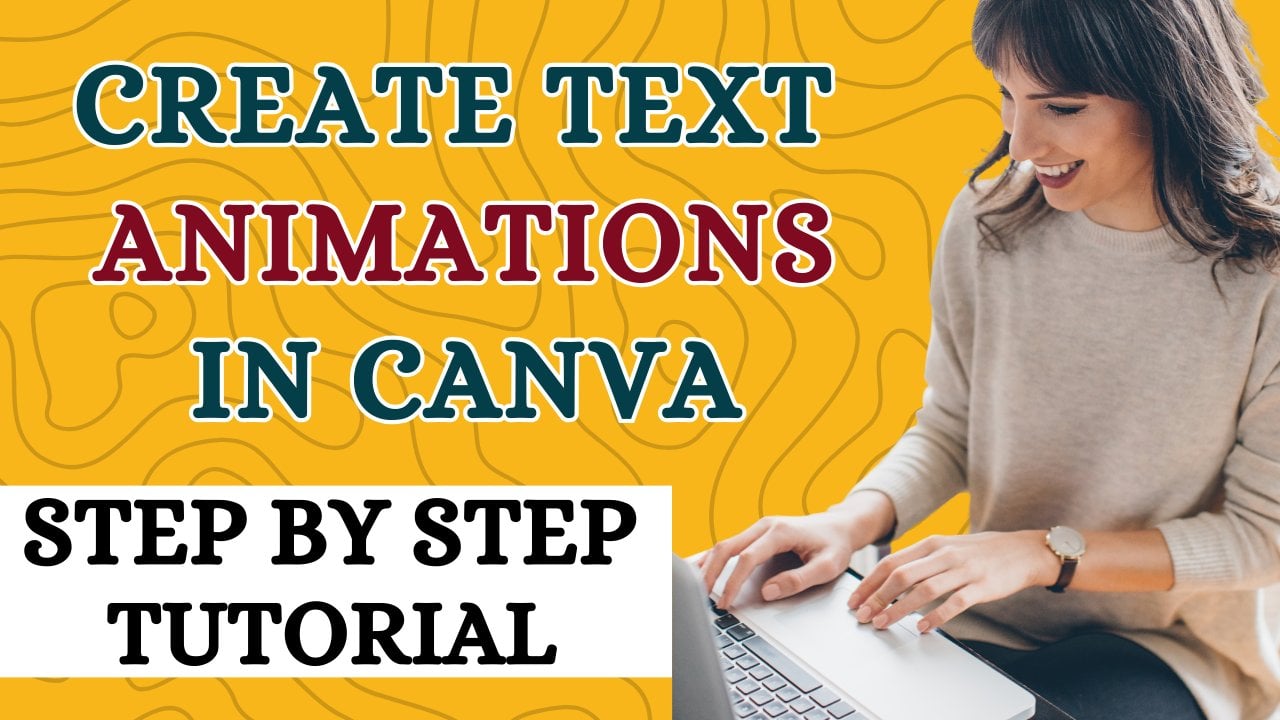
Canva für Anfänger: Lerne Canva-Textanimationen | Einfaches Canva-Tutorial für kinetische Typografie!
Einführung in die Typografie und ihre Typen
4 Prinzipien der Typografie
Animierte typografische Logos in Canva
Verwenden benutzerdefinierter Animationen bei der Logoerstellung
Anwenden benutzerdefinierter Animationen auf Vorlagen
Eine Pro-Technik zum Identifizieren von Schriftdetails
Hinzufügen von Audio zu typografischen Logos
Kursprojektvideo
Entdecke die Macht von Canva und tauche in die dynamische Welt der kinetischen Typografie mit unserem umfassenden Videokurs „Canva für Anfänger: Canva-Textanimationen lernen | Einfaches Canva-Tutorial für kinetische Typografie!“, Egal, ob du ein Anfänger bist oder über Designerfahrung verfügst, dieser Kurs ist darauf zugeschnitten, dass du mit den Fähigkeiten ausrüstest, um atemberaubende animierte typografische Logos mit Canva zu erstellen.
Kursübersicht: In diesem 9 Unterrichtseinheiten umfassenden Kurs führen wir dich durch die Grundlagen der Typografie, führen dich in die Kunst der kinetischen Typografie ein und bieten detaillierte Einblicke in die verschiedenen Arten. Mit dem Fokus auf der praktischen Anwendung baut jede Lektion auf der letzten auf und gipfelt in einem praktischen Projekt, in dem du deine neu gewonnenen Fähigkeiten zum Leben erweckst. Mit diesem Canva-Tutorial lernst du nicht nur Canva-Animationen, sondern machst auch einen Schritt auf dem Weg zum Canva-Pro!
1. Einführung in die Typografie und ihre Typen: Begib dich auf deine typografische Reise mit einer soliden Grundlage. Lerne mehr über die Geschichte der Typografie und erkunde ihre verschiedenen Typen. Verstehe die Bedeutung der Typografie im Design und entdecke, wie sie deine kreativen Projekte verbessern kann.
2. Kinetische Typografie aufgedeckt: Tauche ein in die fesselnde Welt der kinetischen Typografie. Verstehe, wie Text durch Bewegung zum Leben erweckt werden kann, und entdecke die Prinzipien, die eine effektive kinetische Typografie bestimmen. Lass dich von realen Beispielen inspirieren und begreife die Kunst des Storytellings durch bewegten Text.
3. Die 4 Prinzipien der Typografie: Meistere die Grundlagen der Typografie mit dem Fokus auf vier Schlüsselprinzipien: Ausrichtung, Kontrast, Wiederholung und Nähe. Entdecke wie diese Prinzipien zur Erstellung von visuell ansprechenden und wirkungsvollen typografischen Designs beitragen.
4. Erstellen animierter typografischer Logos in Canva: Hol dir praktische Erfahrung, während wir dich durch den Prozess der Erstellung animierter typografischer Logos in Canva führen. Lerne die Tools und Techniken, um deine Designs zum Leben zu erwecken und deine Logos in der digitalen Landschaft hervorzuheben.
5. Benutzerdefinierte Animationsfunktion von Canva: Erkunde die fortgeschrittenen Funktionen von Canva, insbesondere die benutzerdefinierten Animationstools. Entdecke wie du deine typografischen Animationen feinabstimmen und personalisieren kannst, um sicherzustellen, dass sie nahtlos an die Identität deiner Marke oder deines Projekts angepasst sind.
6. Verwenden benutzerdefinierter typografischer Animationen in Logo-Vorlagen: Integriere benutzerdefinierte typografische Animationen mühelos in bereits vorhandene Logo-Vorlagen. Lerne, wie du Vorlagen an deine einzigartige Vision anpassen und verbessern kannst, um Zeit zu sparen, ohne Abstriche bei der Kreativität zu machen.
7. Pro-Technik zum Identifizieren von Schriftdetails: Entdecke eine professionelle Technik zum Identifizieren von Schriftnamen und Familiendetails. Hebe deine typografischen Designs auf, indem du die perfekten Schriftarten auswählst, die mit deiner Marke oder Botschaft resonieren.
1. Klasse Trailer!: Willkommen Lernende. diesem neuen und spannenden Kurs über kinetische Typografie. Ich, Kartik Angrish, Assistenzprofessor für Management, zertifizierter Inhaltsstratege und erfahrener Willkommen zu diesem neuen und spannenden Kurs über kinetische Typografie. Ich, Kartik Angrish, Assistenzprofessor für Management, zertifizierter Inhaltsstratege und erfahrener Cope-Verräter. Ich habe Menschen in den Bereichen Schreiben digitaler Inhalte, Marketing und Grafikdesign geschult , insbesondere im Zusammenhang mit V. In diesem Kurs werde ich Ihnen beibringen, wie Sie die Leistungsfähigkeit von Kanva nutzen können, um atemberaubende animierte Logos zu erstellen, indem Sie die Prinzipien der kinetischen Typografie atemberaubende V. In diesem Kurs werde ich Ihnen beibringen, wie Sie die Leistungsfähigkeit von Kanva nutzen können, um atemberaubende animierte Logos zu erstellen, indem Sie die Prinzipien der kinetischen Typografie anwenden. Ich beginne mit einer Einführung in Typografie und ihre Typen, gefolgt von vier Prinzipien der Typografie mit einem besonderen Schwerpunkt auf kinetischer Typografie Dann werde ich zu animierten typografischen Logos in Canva übergehen typografischen Ich werde Ihnen beibringen, wie Sie benutzerdefinierte Animationen bei der Logo-Erstellung verwenden können benutzerdefinierte Animationen bei der Logo-Erstellung Anschließend werde ich mit Ihnen teilen, wie Sie die Leistungsfähigkeit der Vorlagen in Canva nutzen können , um sehr interessante benutzerdefinierte Animationen zu erstellen Am Ende dieses Kurses werde ich Ihnen eine professionelle Methode vorstellen, mit der Sie Ihre Schrift und ihre Familiendetails identifizieren können Im vorletzten Video werde ich mit Ihnen besprechen, wie Sie Ihren typografischen Logos Musik oder Audio hinzufügen können Ihren typografischen Logos Musik oder Audio hinzufügen Abschließend werde ich mit einem interessanten Projektvideo abschließen , in dem die Fähigkeiten, die Sie in diesem Kurs erworben haben, auf die Probe In diesem Kurs gibt es viel zu lernen. Ich freue mich auf dich in diesem Kurs. 2. Einführung in die Typografie und ihre Typen: Willkommen bei den Lernenden. Willkommen zu diesem Video zur Einführung in die Typografie ist ein sehr umfangreiches Thema, aber für den Zweck dieses Kurses werde ich mich auf die Typografie und ihre Grundprinzipien beschränken , die für die Leinwand relevant sind Es gibt bestimmte Dinge, die verstanden werden müssen, um das Beste aus diesem Kurs herauszuholen Lassen Sie mich zuerst Typografie definieren. Typografie ist ein Begriff, der für den Stil oder das Erscheinungsbild von Text verwendet wird für den Stil oder das Erscheinungsbild von Es ist auch bekannt als die Kunst , mit dem Text zu arbeiten. all diesen in Canva verfügbaren Schriftarten handelt es sich um voreingestellte typografische Sie haben es zur Erleichterung der Benutzer erstellt, damit Benutzer sie problemlos in ihren Text einprägen können Wenn ich zum Beispiel hier drüben klicke, wird diese spezielle Schrift hier angezeigt Ich kann die Größe ändern, die Farbe ändern, ich kann ihr Animationen hinzufügen, so oder so Ich kann dem typografischen Text hier auch einige Effekte hinzufügen. Vielleicht kann ich einen Glitch-Effekt aushöhlen oder hinzufügen, oder ich kann ihn neonfarben machen Ich könnte auch eine Gliederung hinzufügen. Ich kann auch diesen Lift - oder Spleißeffekt verwenden. Oder wenn ich keinen von ihnen haben möchte, kann ich zurück zur Nonne gehen, was der Standardeffekt ist Jetzt wissen Sie, was Typografie ist , und in Canva stehen zahlreiche Optionen zur Verwendung typografischer Elemente zur Verfügung Verwendung typografischer Elemente Lassen Sie mich die Typografie nun in zwei wichtige Segmente einteilen . Das eine ist Ihre statische Typografie, so wie dieser frische Text oder die hier geschriebene Typografie ein Beispiel für statische Typografie ist , bei der Sie eine bestimmte Schrift in einer bestimmten Farbkombination und in einem bestimmten Stil verwendet haben in einer bestimmten Farbkombination und in einem bestimmten Stil so wie dieser frische Text oder die hier geschriebene Typografie ein Beispiel für statische Typografie ist, bei der Sie eine bestimmte Schrift in einer bestimmten Farbkombination und in einem bestimmten Stil verwendet haben. Das ist es Sie können es als PNG-Datei oder als JPG-Datei herunterladen und es ist eine Bilddatei, die Sie verwenden können, wo immer Sie möchten. relevanter für diesen Kurs ist jedoch ein anderer Aspekt der Typografie, nämlich die typografische Animation oder kinetische Was genau ist kinetische Typografie? Lass es mich dir zeigen. Nehmen wir an, ich drücke die Schaltfläche „Animation abspielen“. Hier können Sie diesen Typografie-Text selbst sehen diesen Typografie-Text selbst der ein Beispiel für kinetische Typografie ist Sie können feststellen, dass es sich um eine Videodatei handelt und dass es sich um eine sich bewegende Abfolge von Zeichen handelt eine sich bewegende Abfolge Wenn ich es herunterlade, wird es als MP4-Datei oder als Datei im Videoformat heruntergeladen , nicht als statisches Bild. In diesem Kurs geht es genau um kinetische Typografie, insbesondere im Zusammenhang mit animierten Logos verwendet wird können Sie sehr beeindruckende Logo-Videodateien erstellen Mit Canva und den zahlreichen Funktionen Ich werde im Laufe dieses Kurses zu gegebener Zeit mehr über verschiedene Schriftarten und damit verbundene Themen sprechen Laufe dieses Kurses zu gegebener Zeit mehr über verschiedene Schriftarten und damit verbundene Themen . Ich denke, zur Einführung wissen Sie jetzt was genau Typografie ist und was ihre zwei Grundtypen sind, nämlich statische und kinetische Damit schließe ich dieses Video ab. Im nächsten Video werde ich über vier grundlegende Prinzipien der Typografie sprechen, über vier grundlegende Prinzipien der die sowohl für die statische als auch für die kinetische Typografie relevant sein werden . Stat Wir sehen uns im nächsten Video. 3. 4 Prinzipien der Typografie: Willkommen, willkommen zu diesem neuen Video. In diesem Video werde ich über vier Grundprinzipien der Typografie sprechen über vier Grundprinzipien der Typografie Was sind die vier Prinzipien der Typografie? Lassen Sie mich Ihnen die erste Hierarchie, Führung, Nachverfolgung und Unterschneidung erläutern . Was sind sie Lassen Sie mich nacheinander darauf eingehen, zunächst mit der Hierarchie beginne. Sie dient dazu, den Blick des Lesers zu lenken und Textabschnitten unterschiedliche Gewichte zu verleihen . Man kann die wichtigsten Abschnitte oben erwähnen und sie mit Felsbuchstaben, verschiedenen Stilen oder Farben oder allem zusammen hervorheben verschiedenen Stilen oder Farben oder allem zusammen hervorheben Apropos Führen: Führen ist einfach der Abstand zwischen den Zeilen Sie können sehen, dass zwischen diesen vier Zeigern, Hierarchie, Führung, Nachverfolgung und Urne, ein Leerzeichen diesen vier Zeigern, Hierarchie, Führung, Nachverfolgung und Urne, Die Anpassung dieses Abstands erfolgt durch den Prozess, der in Canva als Leading bezeichnet Es gibt eine sehr einfache Möglichkeit, dies zu tun. Wählen Sie einfach die Textelemente aus, die Sie anpassen möchten, und gehen Sie zur Option Abstand. Hier gibt es sowohl die Option des Buchstabenabstands als auch des Zeilenabstands. Wir beziehen uns auf Leading , also auf Zeilenabstand. Sie können sehen, dass ich es von hier aus anpassen kann. Der Abstand zwischen den Linien nimmt zu. Sie kann auch von hier aus verringert werden. Diese Funktion ist ein nützliches Feature. Wenn Sie bestimmte Schriften verwenden, die in ihrem Design, in ihrem Stil zu überladen ist ein nützliches Feature. Wenn Sie bestimmte Schriften verwenden sind, benötigen sie mehr Abstand zwischen den Zeilen, benötigen sie mehr Abstand zwischen um den Text lesbarer und lesbarer zu machen eleganter Zeilenabstand wird auch als Zeilenabstand bezeichnet Dies ist ein wichtiges Prinzip der Typografie, das Sie beachten müssen Als nächstes folgt das Tracking. Tracking ist eine Ergänzung zum Führen. Tracking ist nichts anderes als Ihr Buchstaben - oder Zeichenabstand. In Canva nennen wir das Buchstabenabstand. Wenn ich ihn von hier aus anpasse, kann ich den Abstand zwischen den Zeichen vergrößern oder verkleinern Auch hier besteht der Zweck darin, Ihren Inhalt zu gestalten, Ihren Text lesbarer, schöner und augenschonender zu Diese beiden wichtigen Prinzipien sind wichtige Elemente der Typografie Das heißt, Leading und Tracking lassen sich in Canva mithilfe der Funktion „Abstand“ ganz einfach in Canva mithilfe der Funktion „ Nachdem das Führen und Nachverfolgen von Hierarchien nun abgeschlossen ist, an vierter Stelle die Unterschneidung. Was genau ist Kerning? Ist sehr eng mit dem Tracking verwandt, es geht aber um Verzerrungen im Abstand Es gibt bestimmte Formen, bei denen ein Abstand zwischen verschiedenen Zeichen besteht , was beim Verkleinern sehr unangenehm aussieht Sie möchten nicht in einer Position sein, in der Sie ein Dokument erstellen, und wenn ein Text einmal verkleinert ist, wirkt er unprofessionell und unattraktiv wirkt er Dieser unvollkommene Abstand zwischen den Zeichen wird auch als schlechter Ring bezeichnet auch Wenn Sie auf eine Schrift stoßen, die schlecht ausgehärtet ist, sollten Sie auf jeden Fall versuchen , diese Schriftart zu ändern, da Sie dadurch möglicherweise nicht die gewünschten Ergebnisse erzielen Seien Sie vorsichtig bei schlechten Schriften. Sie müssen sehr vorsichtig sein dass Leerzeichen zwischen den Zeichen, wie zum Beispiel in dieser speziellen Schrift, hat sie ein sehr gutes n, bedeutet, dass der Abstand zwischen E und E, N, N und N, G alle gleich Es sieht nicht komisch aus, wenn ich es herauszoome. Selbst dann stirbt es nicht, das meine ich Du solltest also bei der Auswahl deiner Schriften sehr vorsichtig sein, damit deine Schriften keine böse List haben dürfen Das sind die vier Prinzipien der Typografie. Ich hoffe, Sie haben sie verstanden und sie werden sich als sehr nützlich erweisen, wenn Sie anfangen, mit kinetischer Typografie zu arbeiten Im nächsten Video werde ich über typografische Logoanimationen in Canva oder die Erstellung kinetischer Typografie mit Canva speziell für die Erstellung dynamischer Logos sprechen typografische Logoanimationen in Canva oder die Erstellung kinetischer Typografie mit Canva speziell für Danke, dass du dir das angesehen hast, lerne weiter. Schau weiter zu. Wir sehen uns im nächsten Video. 4. Animierte typografische Logos in Canva: Willkommen, Lernende. Willkommen zu diesem neuen Video In diesem Video werden wir darüber sprechen, wie wir die Leistungsfähigkeit von Canva nutzen können , um kinetische Typografie für die Erstellung animierter Logos zu erstellen für die Erstellung Va unterstützt eine Vielzahl von Grafiken und Animationen, und kinetische Typografie oder kinetische Logos oder animierte Logos Wie Sie sehen können, verfügt Canva über viele integrierte Animationen für typografische Elemente, mit denen werden können Wir werden sie nacheinander untersuchen, was sie sind und wie du die Leistungsfähigkeit dieser integrierten Animationen nutzen kannst , um atemberaubende kinetische Logos in Canva zu erstellen Lassen Sie mich ein hypothetisches Logo für eine Firma namens Kinetic Yoga erstellen eine Angenommen, dies ist der Name unseres Unternehmens und wir müssen ein animiertes Logo für dieses Unternehmen erstellen Was wir tun werden, ich habe hier Kinetic Yoga mit einfachen Textelementen geschrieben hier Kinetic Yoga mit einfachen Textelementen Was ich damit machen kann, ich wähle einfach zuerst die Effekte aus, um dem Ganzen ein einzigartiges Aussehen und Gefühl zu verleihen Ich sage vielleicht Gliederung, oder das sieht gut aus. Ich kann hier sogar andere Elemente ausprobieren, aber dieser Spleiß sieht gut aus Lassen Sie mich das nur ein wenig vergrößern. Das sieht gut aus. Lass es mich einfach in die Mitte stellen. Bei diesem Text kann ich den Abstand anpassen , da Ihr Logo kompakt sein sollte. Lassen Sie mich den Raum ein wenig reduzieren. Erinnern Sie sich an die grundlegenden typografischen Prinzipien , die ich im vorherigen Video mit Ihnen besprochen habe Lassen Sie mich hier einfach den Abstand zwischen den Buchstaben reduzieren . Das sieht gut aus. Nun, was ich hier tun kann, ich kann einfach auf diese Animate-Schaltfläche klicken Ich werde zu diesem Animationsregal auf Canva weitergeleitet, wo ich meine gewünschte Animation auswählen kann Beachten Sie, dass zwei Arten von Animationen verfügbar sind. Hier sind Animationen auf Seitenebene und eine weitere sind Textanimationen. Wenn ich auf die Seitenanimation klicke, wird alles, was sich auf der Seite befindet als solches animiert. Angenommen, ich hätte zwei Logos , nur um den Seitenanimationseffekt hier zu präsentieren. Da ich kinetisches Yoga hier dupliziert habe, möchte ich noch einmal auf Animation klicken Und ich werde hier auf die Seitenanimation klicken. Welche Animation ich nun auch anwenden werde, sie wird gleichzeitig auf die gesamte Seite angewendet. Das sind die beiden kinetischen Yoga-Elemente, die es gibt. Sie können von hier aus sehen, dass jede Animation, die ich auswähle, auf beide Zeilen hier angewendet wird Das ist der Vorteil von Animationen auf Seitenebene, aber normalerweise hat man nicht mehrere Zeilen. Animationen auf Textebene reichen für Sie aus, falls Sie mehr als zwei Elemente haben. Animationen auf Seitenebene können in Canva sehr praktisch sein. Lass mich das löschen. Den brauchen wir nicht. Nun, mit dem, was ich machen kann, vielleicht könnte ich hier ein Bild haben. Dies ist ein in die engere Wahl gezogenes Bild dieser hypothetischen Firma, Kinetic Yoga Nehmen wir an, das Bild, das ich habe, ist der Text, den ich in meinem Logo Lassen Sie mich sie einfach gruppieren , damit ich sie leicht in der Größe ändern kann Nun, das sieht schon sehr gut aus, aber es ist ein statisches Logo Was wir wollen, wir wollen ein animiertes Logo. Das ist ein Logo im Videoformat. Was wir damit machen können, ich werde diese Gruppe gemeinsam auswählen und hier zum Tab wechseln. Jetzt wird diese gesamte Gruppe animiert , da alle Elemente zusammen gruppiert wurden. Lassen Sie mich dorthin gehen und nehmen wir an, dass ich das wieder benutze. Beachten Sie nun, dass es früher Seitenanimationen und Textanimationen gab. Nun, was ist hier passiert? Die Registerkarte „Textanimation“ wurde automatisch durch eine Fotoanimation ersetzt. Da ich ein Foto zu meinem Logo-Regal hinzugefügt habe, kann ich, wenn ich nur ein Foto animieren möchte, dieses auswählen Andernfalls kann ich die Seitenanimation verwenden, die sich sowohl auf den Text als auch auf das Foto auf der Seite auswirkt Angenommen, ich möchte dieses oder jenes auswählen. Ich kann jeden von ihnen auswählen. Es sind viele Animationen verfügbar. Ich kann mich für eine von ihnen entscheiden. Diese Kombinationen sind zwar ziemlich mächtig und ziemlich elegant, aber ich bin nicht auf sie beschränkt. Ich kann sie jederzeit mit den unten angegebenen Optionen anpassen. Angenommen, ich möchte mich mit der Geschwindigkeit der Animation befassen. Ich kann es von hier aus machen. Ich kann es je nach Fall langsamer oder schneller machen. Es liegt an mir. Ich kann auch wählen, ob ich an beiden Enden animieren möchte. Das heißt, sowohl am Anfang als auch am Ende oder nur beim Betreten oder beim Verlassen Hier gibt es ziemlich viele Variationen. Es gibt hier sogar eine Richtungsvariation, die ich ändern kann, das ist eine Standardrichtung, Richtung nach oben. In dieser speziellen Animation kann ich es nach unten machen, indem ich mich für diesen Pfeil hier entscheide Ich kann diese Optionen hier weiter anwenden , die wenig fortgeschritten sind Aber auch hier geben sie mir die Möglichkeit, mit verschiedenen Bewegungen zu spielen . Sowohl mein Text als auch Fotoelemente sind in meinem Logo enthalten. Diese Ausscheidungen sind hier ganz nett wie Sie von hier aus sehen können Das sieht toll aus, nicht wahr? Auch hier kann ich die Bewegung der ausgeführten Animationen beurteilen , indem ich diese Pfeiltasten verwende, um ihr mehr Abwechslung zu verleihen Sie haben Ihnen die Möglichkeit gegeben diese Bewegungseffekte hinzuzufügen Sie können diesen Rotationseffekt haben. Siehst du, wie toll es aussieht, nicht wahr? Sie können auch einen Flackereffekt, Pulseffekt oder einen Wackeleffekt Erstaunlich, nicht wahr? So können Sie diese animierten Logos mit Canva ganz einfach erstellen diese animierten Logos mit . Wählen Sie einfach den Text und das entsprechende Bild aus Wenn Sie sie möchten, fügen Sie einfach gewünschten Effekt hinzu oder Ihre Schriftart ist gut genug Sie müssen keine gleichmäßigen Effekte hinzufügen Wenden Sie auch einfach eine der eingebauten Animationen an. Hier können Sie sowohl Animationen auf Seitenebene als auch auf Foto - oder Textebene ausprobieren Animationen auf Seitenebene als auch auf Foto - oder Textebene Und was auch immer Ihrem Zweck am besten dient , Sie können es versuchen Es gibt viele Variationen und du kannst sie anhand ihrer Richtung, ihrer Geschwindigkeit und anderer Filter, die sie dir hier gegeben haben, weiter anpassen ihrer Geschwindigkeit und anderer Filter, die sie dir hier gegeben haben So einfach ist es, atemberaubende animierte Logos in Canva zu erstellen atemberaubende animierte Logos in Canva Mit den integrierten Animationsoptionen können Sie jede Art von Logo erstellen gibt es zwar viele Optionen Canva gibt es zwar viele Optionen zum Erstellen animierter Logos Wenn Sie jedoch Ihre eigene Version der Animation erstellen möchten , gibt es dennoch einen Ausweg Im nächsten Video werde ich mit Ihnen besprechen, wie Sie relativ einfach benutzerdefinierte Animationen in Canva erstellen können relativ einfach benutzerdefinierte Animationen in Canva erstellen Wenn Sie es mit anderen komplexen Grafikdesign-Softwares vergleichen , können Sie sich etwas Eigenes einfallen lassen, etwas sehr Einzigartiges, das möglicherweise für Ihren Geschäftszweck erforderlich ist Danke, dass Sie sich das angesehen haben. Lernen Sie weiter, schauen Sie weiter Wir sehen uns im nächsten Video. 5. Verwenden von benutzerdefinierten Animationen bei der Logo-Erstellung: Willkommen, Lernende. Willkommen zu diesem neuen Video In diesem Video werde ich mit Ihnen besprechen, wie Sie die benutzerdefinierte Animationsfunktion von Canva verwenden können , um atemberaubende kinetische Logos zu erstellen Mal sehen, wie wir das machen können. Im letzten Video habe ich mit Ihnen besprochen, wie diese Animationen funktionieren, sowohl auf Elementebene als auch auf Seitenebene. Jetzt werde ich Ihnen eine weitere beeindruckende Funktion von Animationen in Canva vorstellen eine weitere beeindruckende Funktion von , nämlich benutzerdefinierte Animationen Mal sehen, wie wir das machen können. Wenn ich ein Element auswähle, wenn ich mehrere Elemente oder eine Seite als Ganzes auswähle, gibt es hier die Möglichkeit, die Animation zu schwenken. Wir kennen diesen Bereich inzwischen, aber es gibt noch eine weitere Option, um oben eine Animation zu erstellen. Dies ist eine benutzerdefinierte Animationsfunktion von Canva. Es ist eine sehr leistungsstarke Funktion. Es gibt Ihnen die Möglichkeit, Ihre eigene Version von Animationen gemäß Ihren Anforderungen und Ihrer Kreativität zu erstellen. Mal sehen, wie es funktioniert. Angenommen, ich wähle hier dieses einzelne Element aus und klicke auf Registerkarte Animation erstellen. Es gibt mir die Möglichkeit, meinen eigenen Animationspfad zu entwerfen. Ich kann diesen Text nach meinen eigenen Wünschen und meiner Kreativität verschieben , ihn platzieren, wo immer ich will, und dieser Pfad wird als animierter Pfad nachgezeichnet Sie können sehen, wie dieser animierte Pfad funktioniert. Nun, das war nur, um Ihnen darüber zu erzählen Beachten Sie das hier, da ich im Animations-Tab einen benutzerdefinierten Animationspfad ausgewählt hatte , ist er hier benutzerdefiniert geschrieben. Wenn mir das nicht gefällt, kann ich es sicherlich ändern. Angenommen, ich möchte den Pfad löschen. Ich kann es einfach von hier aus machen. Das Element, für das der Animationspfad gelöscht werden muss, muss ausgewählt werden. Ich habe hier kinetisches Yoga ausgewählt. Und ich werde diesen Pfad auf einmal löschen. Der gesamte Pfad wurde auf die Standardwerte zurückgesetzt. Das heißt, hier gibt es keine Animation. Wie Sie sehen können, ist es animiert geschrieben. Anstatt benutzerdefiniert bedeutet das, dass keine Animation im Spiel ist Auch hier kann ich dasselbe auf mehrere Elemente anwenden . Lass es mich dir hier ganz schnell zeigen. Ich wähle hier beide Elemente aus und klicke auf die Option Animieren. Und dann gehe ich zur Animation erstellen. Von hier aus wähle ich einen Pfad für alle Elemente zusammen aus. Jetzt sieh dir das an, lass es mich für dich spielen. Siehst du das, wie es funktioniert? Dies diente nur dazu, die Funktionalität dieses benutzerdefinierten Animationspfads zu demonstrieren . Nun stellt sich die Frage, wie man es effektiver einsetzen kann, um professionelle, großartige und dennoch einzigartige benutzerdefinierte Animationen zu erstellen . Wir werden in diesem Video darüber sprechen. Jetzt habe ich dieses kinetische Yoga hier ausgewählt. Ich möchte es nicht nach dem Zufallsprinzip bewegen , weil es nicht professionell aussieht Was ich tun werde, ich werde hier eine weitere Funktion anwenden. Lassen Sie mich jetzt einfach die Schritte hier durchgehen , damit ich eine Umschalttaste auf meiner Tastatur gedrückt halten und diese dann bewegen kann. Es wird sich in der geraden Linie bewegen. Wenn ich es sanft in eine der beiden Richtungen bewege, nehmen wir an, ich bewege es nach Norden, dann können Sie sehen, dass es sich um eine gerade Linie Ich bringe es langsam in die ursprüngliche Position zurück und belasse es dort Sehen Sie sich jetzt an, wie diese Animation funktioniert. Das ist viel besser als die zufällige Bewegung. Gut, nochmal, ich lösche diesen Pfad. Ein weiteres wichtiges Merkmal der benutzerdefinierten Animation. Wie bei anderen Animationen , die wir bisher gesehen haben, können wir sie hier in Verbindung mit den Bewegungseffekten verwenden . Lassen Sie mich Ihnen zeigen, wie wir das machen können. Nehmen wir an, ich wähle dieses Foto hier und gehe dann zur Schaltfläche Animieren, und da drüben gibt es Bewegungseffekte. Gut, was ich tun werde, ich werde einen der Bewegungseffekte anwenden Ich kann mehrere Bewegungseffekte anwenden. Siehst du, ich habe „Flackerperlen drehen“ ausgewählt. Ich kann dem sogar Wackeln hinzufügen und einfach sehen, wie es funktioniert. Es sind mehrere Bewegungseffekte im Spiel. Aber auch hier übertreibt es die Dinge. Es ist nicht ratsam, was ich tun werde, ich wähle hier einen Bewegungseffekt und entferne alle anderen Bewegungseffekte Lass mich wackeln. Ich entferne auch den Rotationseffekt. Sie müssen jeden Effekt einzeln entfernen. Ich werde entweder den Puls halten oder flackern. Angenommen, ich habe mich für Flicker entschieden. Mit Flicker geht es so, oder ich kann den Puls halten und das Flimmern entfernen Jetzt wird es so aussehen. Das sieht besser aus. Lass mich diesen Pulseffekt behalten. Gehen Sie jetzt zur Option Animieren. Klicken Sie auf Animation erstellen, benutzerdefinierte Animation und drücken Sie die Umschalttaste Jetzt werde ich dieses kinetische Yoga ein wenig nach oben bewegen. Ich klicke hier auf Fertig und sehe, wie es ganz sanft herauskommt Dieser kinetische Yoga-Text bewegt sich ein wenig nach oben und gleichzeitig pulsiert dieses Bild zusammen Mit diesen beiden Effekten erhalte ich eine professionell aussehende Animation Lassen Sie mich Ihnen zeigen, wie es funktioniert. Lass mich einfach diese kinetische Yoga-Animation verbessern. Ich bringe es auch wieder an die ursprüngliche Position , damit es wieder an seinen ursprünglichen Platz kommt Lassen Sie mich hier auf die benutzerdefinierte Animation klicken. Ich werde den Pfad löschen. Und jetzt drücke ich erneut die Shift-Taste und bewege sie leicht nach oben. Und bringe es in der geraden Linie nach unten , während du die Shift-Taste gedrückt hältst. Nun sieh mal, so kommt es. Lassen Sie mich jetzt einfach die Geschwindigkeit dieser Animation erhöhen. Ich kann die Geschwindigkeit von benutzerdefinierten Animationen steuern , wie ich es mit den anderen Animationen tun kann. Ich werde die Geschwindigkeit erhöhen weil es ein bisschen ruckelig ist Und das liegt daran, dass es nicht einfach ist , ein Element in einer geraden Linie zu bewegen, selbst mit der Shift-Taste wird die Richtung mit der Shift-Taste gesteuert, aber das Tempo wird sicherlich nicht konsistent sein Um das zu tun, kann ich es entweder mit Smooth oder Steady versuchen. Ich denke, Studium funktioniert am besten. Ich entscheide mich für die Studienoption und klicke hier auf Fertig. Einfach Teller. Mal sehen, wie es jetzt funktioniert. Viel besser. Jetzt hat sich kinetisches Yoga sanfter und schneller nach oben entwickelt Und wenn man mit wenig Übung zu seiner ursprünglichen Position zurückkehrt, mehr oder weniger zu seiner ursprünglichen Position , wird man sie sicherlich verbessern Aber es geht darum, Ihnen eine Vorstellung davon zu geben, wie benutzerdefinierte Animationen funktionieren und wie Sie mit Ihren Logos Ihre eigene einzigartige Art von Animationen erstellen können Ihren Logos Ihre eigene einzigartige Art von , bei denen Sie Bilder und Textsegmente separat animieren Und sicherlich auch als Ganzes. Das war es in diesem Video, in dem ich Ihnen die benutzerdefinierte Animationsfunktion von Canva erklärt habe , mit der Sie atemberaubende animierte Logos mit schlechten Text- und visuellen Elementen erstellen können mit schlechten Text- und visuellen Elementen Im nächsten Video werde ich den gleichen Prozess mit einigen der etablierten Logo-Vorlagen durchführen den gleichen Prozess mit einigen der etablierten Logo-Vorlagen Denn wenn Sie Ihre eigenen Logos erstellen, können Abmessungen manchmal ein Problem sein. Wenn Sie eine Vorlage für die Logoerstellung verwenden, sind die Abmessungen viel besser aufeinander abgestimmt und Sie können eine beliebige Vorlage auswählen beliebige Vorlage , die Ihren Geschäftszielen entspricht. Im nächsten Video zeige ich dir den Prozess anhand einer Vorlage und wie wir mit dieser benutzerdefinierten Animationsfunktion mit Logo-Vorlagen herumspielen und tolle kinetische Logos in Canva erstellen können dieser benutzerdefinierten Animationsfunktion mit Logo-Vorlagen herumspielen und tolle kinetische Logos in Canva erstellen Danke, dass du dir dieses Video angesehen hast. Seien Sie gespannt auf das nächste Video. 6. Anwenden benutzerdefinierter Animationen auf Vorlagen: Willkommen, Lernende. Willkommen zu diesem neuen Video In diesem Video werde ich mit Ihnen besprechen, wie Sie Logo-Vorlagen mit benutzerdefinierten Animationen in Canva ändern können Logo-Vorlagen mit benutzerdefinierten Animationen in Canva ändern Lassen Sie mich hier nach animierten Logo-Vorlagen suchen. Ich habe hier ein animiertes Logo geschrieben und werde hier klicken. Schau, was es mir zeigt. Dies sind die Vorlagen , die mir angezeigt werden. Ich kann mir eine davon aussuchen. Für dieses Video werde ich mich von meinem kinetischen Yoga-Thema entfernen und ein anderes Thema verwenden, das Donut-Template, bei dem es sich um ein vorgefertigtes animiertes Logo handelt Was ich tun werde, ich werde es meine eigenen Anforderungen optimieren Was meine eigene Kreativität angeht, lassen Sie mich einfach hier klicken und diese Vorlage ist geladen und ich werde sie anpassen Lassen Sie mich Ihnen zunächst zeigen, wie diese Animation, die hier die Standardanimation ist, funktioniert Wenn Sie es analysieren, sind hier mehrere eingebaute Animationen im Spiel. Wenn ich dieses spezielle Element auswähle, kannst du sehen, dass es eine Basisanimation hat Dieses D hat eine Burst-Animation. Die Nüsse haben auch eine Burst-Animation. Dieser Boreslin hat keine Animation. Wir werden es optimieren. Wir werden es ändern. Der Denkprozess von Asperaur und die Kreativität von Asperaur. Mal sehen, wie wir das machen können. Was ich zuerst tun werde, sie alle auszuwählen und bestehende Animationen zu entfernen. Ich klicke hier und es gibt die Option einer klaren Animation. Sobald ich darauf klicke, sind alle Animationen in dieser speziellen Vorlage verschwunden. Lass es mich einfach abspielen und um dir zu zeigen, dass es im Moment keine Animation hat. Sie können feststellen, dass es überhaupt keine Animation gibt. Dies kann mit dieser Animationsschaltfläche bestätigt werden, da die Schaltfläche „ Animieren“ nur angezeigt wird, wenn keine Animation vorhanden ist Normalerweise wird es nach dieser Animation benannt, sei Basislinie, benutzerdefinierter Anstieg oder eine andere Was wir jetzt tun werden, ich spiele zuerst mit diesem O, das hier die Form eines Donuts Und schau, wie ich es modifizieren kann. Ich werde diesen Dreh- und Impulsbewegungseffekt hier für dieses spezielle Element verwenden , nämlich O in Form eines Donuts Jetzt ändere ich diesen Text zunächst davon ausgehe, dass mein Markenname Donut Cafe ist Ich ändere dieses Porzellan in Café. Ich kann die Schriften ändern , wenn sie mir nicht gefallen. Angenommen, ich entscheide mich dafür, das sieht besser aus. Vielleicht ändere ich die Farbe und mache sie heller. Das sieht nett aus. Jetzt werde ich eine sehr interessante Funktion in Canva verwenden , nämlich Hilfslinien und Lineale Das hilft mir zu verstehen, wo sich meine Elemente befinden und wo ich sie nach der Animation platzieren kann , damit es im Endprodukt nicht zu unerwünschten Verzerrungen Lassen Sie mich Ihnen zeigen, wie wir das machen können. Klicken Sie auf die Option Datei, gehen Sie zu Einstellungen, Lineale und Hilfslinien anzeigen Sobald ich auf Lineale und Hilfslinien geklickt habe, kann ich die Positionen genau bestimmen, wo Sobald ich die Elemente ändere, kenne ich ihre Was ich von hier aus tun werde, ist, dass ich es um eine horizontale Linie hierher ziehe . Ich ziehe eine weitere, um die ursprüngliche Position meines Cafés zu markieren . Zeichne noch eine Linie. Donuts hier an die Spitze , weil hier das höchste Element ist Mein Donut und mein Café sind an diese horizontalen Linien gebunden. Lassen Sie mich jetzt auch einige vertikale Linien hinzufügen, um dieses D zu markieren. Okay, jetzt weiß ich, wo meine ursprünglichen Textelemente sind Ich möchte, dass sie sich am Ende der Animation an derselben Position befinden, unabhängig davon, welche Animation ich für sie erstelle Als Nächstes platziere ich dieses Café in der Mitte des Bildschirms Es ist bereits in der Mitte. Ich lege es in die Mitte. Wie ich das machen kann, wähle einfach das aus. Gehe zu der Position und sie ist, sie ist schon in der Mitte der Seite. Die Mitte ist von links nach rechts und die Mitte ist von oben nach unten. Ich möchte es sowohl in der Mitte als auch in der Mitte haben. Ich klicke hier. Nun, dieses Café befindet sich in der Mitte als auch in der Mitte. Falls Sie mit all diesen Bearbeitungsfunktionen in Canva noch nicht vertraut sind , können Sie sich meinen Kurs auf dieser Plattform über Bearbeitungsfunktionen und Canva-Hacks ansehen , in dem alle Bearbeitungsfunktionen einfach erklärt und es gibt tolle Beispiele, die den Lernenden helfen . Schau dir diesen Kurs an, falls du noch nicht mit Canva vertraut bist Falls das für dich nicht neu ist , wird dieser Kurs, in dem es um das Bearbeiten von Hacks geht, deine Wissensbasis sicherlich bereichern und du wirst besser werden, wenn dieser Kurs, in dem es um das Bearbeiten von Hacks geht sicherlich bereichern deine Wissensbasis sicherlich bereichern und du wirst besser werden Leute, die Canva Bar checken zu diesem speziellen Projekt zurückkehren Was ich jetzt tun werde, ich werde hier ein Rechteck hinzufügen. Ich klicke auf den Bildschirm und drücke R und erweitere dieses Rechteck, sodass es die Abmessungen meines Logos vollständig abdeckt. Ich ändere die Farbe dieses Rechtecks in die Grundfarbe dieser Vorlage, sodass es unsichtbar ist. Ich lege es wieder zurück. Ich werde die Position nutzen. Gehe zu Ebenen und setze es hinter Cafe, dass mein Café sichtbar ist, der Rest der Elemente ist nicht sichtbar. Was ich nun tun werde, ich wähle dieses Café aus und gehe zur Option Animieren Siehst du, es ist noch nicht animiert. Deshalb ist Animate hier drüben geschrieben. Ich klicke hier. Jetzt wähle ich eine Animation erstellen, bei der es sich um eine benutzerdefinierte Animation handelt. Äh, und drücke die Umschalttaste. Erinnere dich daran aus dem vorherigen Video. Ich drücke die Umschalttaste, damit sie in der geraden Linie nach unten geht. Was ich hier machen werde, ich wähle dieses Café aus und gehe zu dieser Animate-Option Wählen Sie „Animation erstellen“. Und drücken Sie hier die Umschalttaste. Und ziehe es langsam an seine ursprüngliche Position in der geraden Linie. Mach dir nur keine Sorgen über das Tempo. Es kann jederzeit mit einer gleichmäßigen und gleichmäßigen Funktion eingestellt werden . Auch hier werde ich mich für das stabile Modell entscheiden und sehen, wie schön es ist, wenn es von der Mitte des Bildschirms aus wieder in seine ursprüngliche Position gebracht wird. Was ich nun tun werde, ich werde dieses Kästchen hier auswählen, das Rechteck, das ich über dieses Logo gelegt habe. Und klicken Sie hier auf die Animationsoption. Drücken Sie erneut die Umschalttaste und ziehen Sie sie nach oben. Und lass es hier liegen, damit mein Donut zum Vorschein kommt. Was ich tun werde, ich werde einfach das Tempo dieser Bewegung dieses Rechtecks erhöhen , damit es sich etwas schneller bewegt Lass mich sehen, ob es hier gut läuft. Okay, ich glaube, ich muss auch das Tempo in diesem Café ändern . Lass es mich auch ein bisschen schneller machen und sehen, wie es jetzt funktioniert. Etwas schneller. Ich spiele wieder. Es ist besser. Sie müssen mehrmals versuchen, das Tempo der verschiedenen Animationen anzupassen. Vor allem, wenn diese Animationen in eine andere Richtung zeigen oder von unterschiedlicher Art sind , sodass sie am besten synchron zusammen funktionieren Sie spielen sich nicht gegenseitig aus oder übertreffen sich gegenseitig. Sie müssen sie synchronisieren und verschiedene Tempoeinstellungen für verschiedene Elemente ausprobieren , bis Sie eine finden , die Ihre Sinne anspricht Ich denke, dieser hier ist in Ordnung. Okay, was kann ich jetzt noch tun? Vielleicht kann ich in diese Position gehen und etwas mit den Nüssen machen. Lass mich diese Nüsse hier animieren. Lass mich Bust oder vielleicht Bounce hinzufügen. Bust sieht besser aus, aber auch hier werde ich die Intensität oder das Tempo anpassen Lassen Sie mich es einfach ein wenig reduzieren und schauen, ob es würziger wird Lassen Sie mich hier alle Elemente auswählen und zu den Effekten übergehen Und ich werde hier einen Glitch-Effekt hinzufügen und sehen, wie er funktioniert. Jetzt müssen Sie es mit verschiedenen Optionen versuchen. Sie können einige der Animationen und einige Ihrer benutzerdefinierten Animationen verwenden. In Verbindung damit können Sie ein einzigartiges animiertes Logo erstellen, bei dem es sich um eine wunderschöne Videodatei handelt , die gut zu Ihrer Markenbotschaft passt und Ihren Zweck erfüllt. Mach dir keine Sorgen um die Führer und Herrscher. Sie werden in den endgültigen Animationen nicht gezeigt. Laden Sie die Datei einfach als MP-Fileshare-Option herunter. Klicken Sie einfach hier. Gehe zum Download. ist MP vier, da es sich um eine Videodatei handelt. Wenn es sich um eine Pro-Version handelt, können Sie deren Qualität und Größe gegenüber den ursprünglichen 500.500 Pixeln verbessern . Ich kann es vielleicht 960 mal 960 Pixel machen. Laden Sie es herunter und Ihre Datei wird auf Ihr System heruntergeladen, von wo aus Sie sie verwenden können, wo immer Sie wollen. Das war es inzwischen in diesem Video. Ich hoffe, Sie kennen sich mit kinetischen Animationen aus und wissen, wie Sie sowohl benutzerdefinierte als auch integrierte kinetische Animationen in Canva verwenden können integrierte kinetische Animationen in Canva atemberaubendes Logo für Ihr Unternehmen zu erstellen Im nächsten Video werde ich mit Ihnen Techniken besprechen, mit denen Sie gewünschte Schriftart für Ihre Logoanimation finden Seien Sie gespannt auf das interessante Video, das als Nächstes erscheint . Wir sehen uns im nächsten Video. 7. Eine professionelle Technik zum Identifizieren von Schriftdetails: Willkommen, willkommen zu diesem neuen Video. Bisher haben Sie gelernt, wie Sie kinetische Typografie oder typografische Textanimationen verwenden können, um atemberaubende Videologos zu erstellen Und ich bin mir sicher, dass Ihnen dieser Kurs gefallen hat und Sie einige nützliche Fähigkeiten erworben haben und Sie einige nützliche Fähigkeiten erworben Wenn das der Fall ist, sollten Sie erwägen, diesen Kurs erneut zu lesen. Weil Ihr positives Feedback und Ihre positive Bewertung mir helfen können, mehr Studierende zu erreichen , die möglicherweise ähnliche Inhalte benötigen. Um zum Thema dieses Videos zu kommen: Es wird Situationen geben, in denen Sie irgendwo im Internet oder auf andere Weise eine Schrift sehen und sie einfach lieben Du möchtest diese Schrift in deinen typografischen Animationen oder in deiner Arbeit auf Canva verwenden deinen typografischen Animationen oder in deiner Arbeit auf Sie stehen vor einem Dilemma. Sie kennen den Namen der Schrift nicht, Sie kennen die Schriftfamilie nicht Du weißt nicht , ob diese Schrift kostenpflichtig oder kostenlos ist oder ob sie in Canva verfügbar ist oder nicht Um dieses Dilemma zu lösen, werde ich Ihnen in diesem Video ein sehr spannendes Tool Ihnen in diesem Video ein sehr spannendes Das Tool trägt den Namen Font. Es ist eine Erweiterung , die sowohl für Chrome als auch für Microsoft Edge oder auch für alle anderen gängigen Browser verfügbar sowohl für Chrome als auch für Microsoft Edge ist. Lassen Sie mich Ihnen nur zeigen, wie Sie diese Erweiterung verwenden und ganz einfach herausfinden können , welche Schriftart Sie in Ihren Animationen verwenden möchten Was Sie tun müssen, schreiben Sie einfach eine Schrifterweiterung für Ihren Browser In der Adressleiste Ihres Browsers. Klicken Sie auf die entsprechende Option, normalerweise steht sie oben. Fügen Sie einfach die Erweiterung ich bereits in meinem Browser hinzugefügt habe. Es zeigt mir also die Option zum Entfernen. Sonst wäre es dort geschrieben worden. Klicken Sie einfach auf die Schaltfläche Abrufen und diese Erweiterung wird heruntergeladen und in Ihre Adressleiste hochgeladen. Wie hier ist dies das Symbol für die Schrifterweiterung. Wie Sie sehen können, wird angezeigt, welche Schriftart, wenn ich mit der Maus darüber fahre Nun, was du tun musst. Gehe zu einer beliebigen Website. Angenommen, ich werde Sie zu dieser Website weiterleiten und auf diese Erweiterung klicken. Es wird deutlich erwähnt , welche Schriftart Zugriff auf diese Website hat. Was Sie tun müssen, Sie müssen lediglich den Cursor auf ein beliebiges Textelement auf Ihrer Seite Hier wird Ihnen der Name der Schrift angezeigt. Wenn ich hier klicke, kann es mir die Details über die Schrift und ihre Familie zeigen. Diese Schrift wird auch Roboto-Slab genannt. Der Sensif-Stil ist normal und das Gewicht beträgt 400. All diese Informationen sind verfügbar. Sogar die Farbe und Größe der Schrift werden hier erwähnt. Mit diesem Tool können Sie jede Schriftart herausfinden. Lassen Sie mich ein anderes Beispiel versuchen. Hier habe ich diese Amazon-Seite geöffnet. Ja, es hat auch Zugriff auf diese Site. Lassen Sie mich darauf klicken und sehen, dass hier die Amazon-Bernsteinschrift verwendet wird. Sie können sehen, dass es erwähnt wird. Jetzt werde ich weiter darauf klicken , um die Details zu erfahren. Auch hier ist das Gewicht 400, der Stil ist normal, Größe ist 14 Pixel, Linite ist 20 Pixel und Farbe wird hier auch erwähnt Sie nun tun, wenn Sie den Namen der Schrift kennen Was müssen Sie nun tun, wenn Sie den Namen der Schrift kennen? Gehen Sie einfach, angenommen, ich möchte diesen Amazon Amber in meinem Canva verwenden diesen Amazon Amber in meinem Canva Was ich tun werde, ich gehe zu Google suche einfach nach Amazon Amber Font Es gibt genügend Websites wie Coupon-Schriften oder CDN-Schriftarten, die Ihnen eine Reihe von Schriftarten kostenlos zur Verfügung CDN-Schriftarten, die Ihnen eine Reihe von Schriftarten kostenlos zur Und es gibt auch kostenpflichtige Schriftarten auf dem Markt. Wenn es kostenlos erhältlich ist, können Sie es herunterladen und einfach in Ihr Canva hochladen, um es in Ihren Animationsprojekten oder auf andere Weise zu verwenden Ihren Animationsprojekten oder auf andere Weise So einfach und unkompliziert ist es. Ich bin mir sicher, dass Sie sich ab jetzt keine Gedanken mehr darüber machen müssen, um welche Schriftart es sich handelt, wenn Sie eine Schrift mögen Gedanken mehr darüber machen müssen, um welche Schriftart es sich handelt, wenn Sie eine Schrift Verwenden Sie einfach dieses Tool und finden Sie den Namen und die Abmessungen der verwendeten Schrift heraus Und versuche, es für dein zukünftiges Projekt herunterzuladen und in dein Canva hochzuladen es für dein zukünftiges Projekt herunterzuladen und in dein Canva Das war es in diesem Video. Im nächsten Video werde ich Ihnen eine professionelle Technik vorstellen, mit der Sie Ihren kinetischen Typografieprojekten Musik hinzufügen können, sodass Ihre Videologos auch Musikelemente enthalten können Lernen Sie weiter, schauen Sie weiter zu. Wir sehen uns im nächsten Video. 8. Audio zu typografischen Logos hinzufügen: Willkommen, Lernende. Willkommen zu diesem neuen Video Bisher haben wir in diesem Kurs gelernt, wie wir atemberaubende animierte Logos erstellen können , sowohl mit Vorlagen als auch von Grund auf neu. Canva ist in beiden Fällen ein großartiges Tool, um kinetische Logos zu erstellen. Da wir nun über animierte Logos sprechen, sprechen wir im Wesentlichen über Videodateien Wenn es eine Videodatei gibt, sollte es die Möglichkeit geben, Audio oder Musik hinzuzufügen. Dadurch kann Ihr kinetisches Logo ansprechender und effektiver Mal sehen, wie wir das machen können. Zum Beispiel werde ich es noch einmal zu meiner Kinetic-Yoka-Vorlage zurückkehren Dies ist dasselbe animierte Kinetic Yoga-Logo , das ich für diesen Kurs erstellt habe Lass es mich einfach ohne Musik abspielen, nur um dir einen Bezugspunkt zu geben Wie Sie sehen können, hat es keine Musik oder Audio im Hintergrund. Bevor ich relevante Musik hinzufüge, möchte ich die Länge etwas erhöhen , da fünf Sekunden für ein musikalisches Logo zu klein sind. Lassen Sie mich das ein wenig ankündigen. Ich lasse es 10,5 oder 13,5 sagen. Gut. Wir können uns jederzeit an die Strecke anpassen, die wir wählen Lassen Sie mich eine passende Audiodatei dafür finden. Ich werde mich für Meditationsmusik entscheiden. Lass mich sehen, wie es funktioniert. Lass mich sehen, ob etwas anderes besser funktioniert. Ich lösche diesen von hier. Lassen Sie mich das sofort plattieren , es sieht besser aus als das vorherige. Ich werde mich für diesen entscheiden. Lassen Sie mich das schließen und hier noch eine Anpassung vornehmen. Es gibt eine Option namens Beat Sync. Wenn es darum geht, Audiovideos in Canva hinzuzufügen, verwende ich einfach diese Option und schaue, was sie für mich tun wird Wenn wir diese Taste betätigen, passen wir die musikalischen Beats an die Bewegung in der Animation Lass mich sehen, ob es jetzt besser klingt. Ja, es ist eindeutig besser als Sync, es klingt und sieht viel besser aus. Was ich jetzt tun werde, ich gehe einfach zur Schaltfläche Shear und klicke auf die Download-Option Standardmäßig steht MP zur Auswahl. Ich behalte das so wie es ist und lade es in mein System herunter. Sobald es auf mein System heruntergeladen ist, kann ich es überall hochladen und es als mein musikalisches Logo für die Marke Kinetic Yoga verwenden als mein musikalisches Logo für die Marke Kinetic Yoga Das war es in diesem Video. Ich hoffe, dir hat diese Funktion gefallen. Ich bin mir sicher, dass Sie sich jetzt viel sicherer fühlen werden , wenn Sie Canva verwenden, um Ihre animierten Logos oder kinetische Typografie im Allgemeinen zu erstellen oder kinetische Typografie Danke, dass du dir dieses Video angesehen hast. Im nächsten Video werde ich mit Ihnen ein sehr interessantes Projekt für diesen Kurs besprechen , bei dem Sie ein einfaches animiertes Logo mit einer Vorlage Ihrer Wahl erstellen müssen . Danke, dass du dir das angesehen hast. Wir sehen uns im nächsten Video. 9. Projektvideo: Begrüßen Sie die Lernenden zum Projektvideo dieses Kurses. Du musst ein kinetisches Logo mit einer der in Canva verfügbaren kinetischen Logo-Vorlagen erstellen Was du tun musst, gehe einfach in die Suchleiste von Canva und gib Es gibt Unmengen von Logo-Vorlagen , die kinetischer Natur sind Sie können eine beliebige auswählen. Ich würde vorschlagen, ein minimalistisches Logo zu wählen, damit Sie ein kompaktes und dennoch wirkungsvolles kinetisches Logo haben Sie können annehmen, dass dieses, ich habe das als Beispiel ausgewählt, was Ihnen erwartet wird, den Text ändern Indem du die Elemente auswählst so wie ich es dir in diesem Kurs beigebracht habe. Fügen Sie vielleicht ein passendes Bild hinzu oder Sie können dasselbe Bild mit verschiedenen Farben und Farbtönen auswählen mit verschiedenen Farben und Farbtönen Es liegt an Ihrer Kreativität und Ihren Anforderungen. Sie können sich dafür entscheiden, ein Logo für Ihr echtes Unternehmen oder ein hypothetisches Unternehmen zu erstellen Ihr echtes Unternehmen oder ein hypothetisches Sie haben die volle Freiheit, entdecken Sie alle Animationsoptionen, verwenden Sie benutzerdefinierte Animationen oder Sie können integrierte Animationen verwenden Es geht darum, ein effektives kinetisches Logo zu erstellen ein effektives kinetisches Logo , das Ihre erworbenen Fähigkeiten auf die Probe In diesem Kurs werde ich jedes eingereichte Projekt bewerten und Ihnen mein Feedback dazu geben Ich freue mich auf Ihre Beiträge. Und zum Schluss möchte ich mich bei Ihnen dafür bedanken, dass Sie sich für diesen Kurs entschieden haben, um kinetische Logoanimationen in Canva zu lernen alles Gute für Ihre Projekte — und atemberaubende kinetische Logos, und atemberaubende kinetische Logos die Sie im Laufe Ihrer Karriere erstellen werden